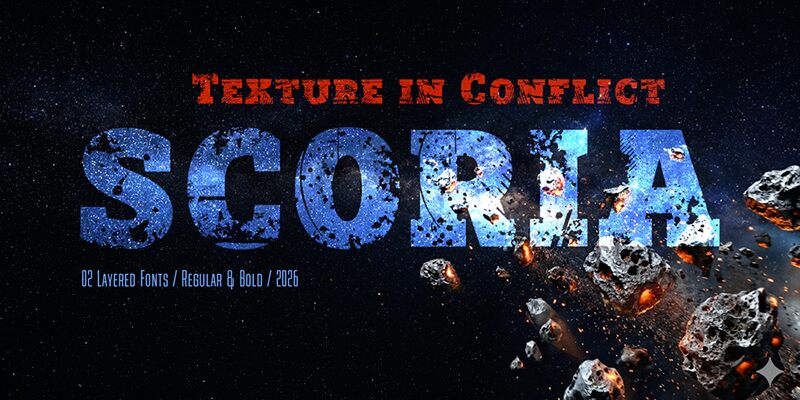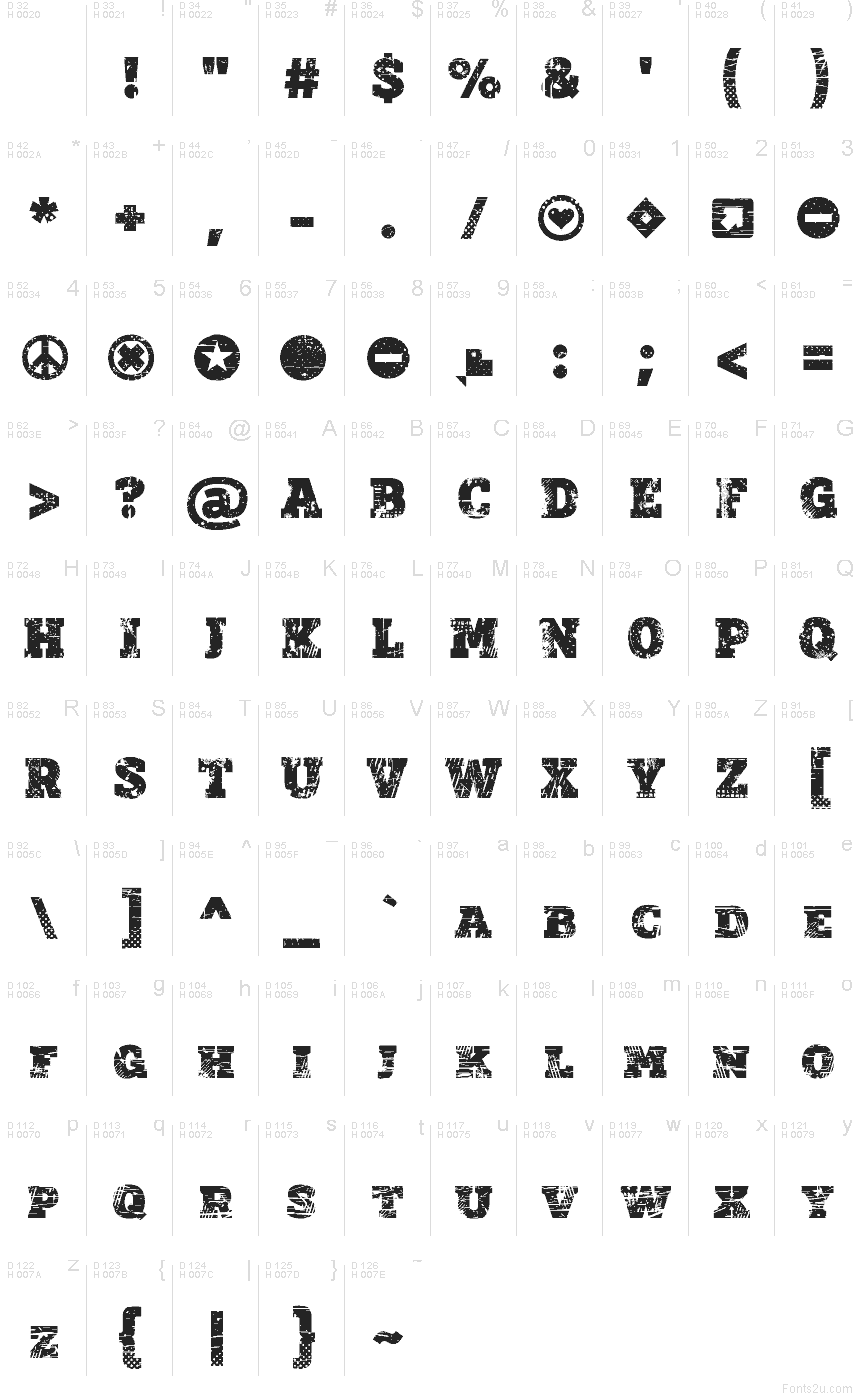
Scoria od deFharo je bezplatné display písmo s erodovaným efektem, které se vyznačuje masivními, těsně sázenými verzálkami a neotesanou industriální siluetou. Jeho hrubost vychází z husté směsi škrábanců, odštěpků, cákanců a proužkovaných řezů, takže opotřebení působí vrstveně a nikoli jednolitě.
Jeho nejpřirozenějším uplatněním jsou koncertní plakáty. Oprýskaný povrch se skvěle hodí také na obaly punkových alb, skate merchandise a grafiku hororových akcí, protože každé písmeno působí jako seškrabaný a těžce zkoušený tisk. Osloví zejména příznivce hudby a streetwearu, kteří vyhledávají agresivní ruční grafiku.
Scoria was born as a typographic relic rescued from a devastated landscape of a torn world.
Its presence is aggressive, heavy, and profoundly expressive, like a fragment of industrial architecture surviving a catastrophe. It screams from the depths of its broken and eroded texture. Each letter seems to carry scars, cracks, and memory, in a declaration of typographic rebellion that adapts to the most intense and urban contexts, a symbol of resistance amidst chaos.
One of Scoria's most distinctive features is its layered font system. I designed the Regular and Bold versions as inseparable companions to work together in overlapping, allowing for the creation of purely typographic headlines in two or more colors with enormous visual impact.